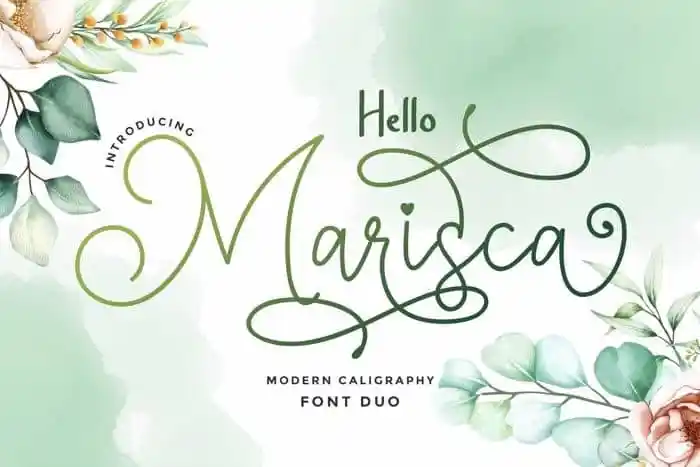
Hello Marisca Script Font – Fonte Grátis
Hello Marisca Script Font
Agora está disponível no mercado a “Hello Marisca Script Font”, uma elegante tipografia que pode ser interpretada de forma profissional. Este tipo de letra é perfeito para aqueles que desejam uma adicional de personalidade e sofisticação em seus projetos, permitindo uma mistura entre um script regular e várias alternativas de letras minúsculas para criar ligaturas únicas. A fonte foi criada e compartilhada pelo Designer Rantautype. Este tipo de letra moderna, feminina e atrativa está aqui para ajudá-lo a elevá-los a um novo patamar em seus trabalhos, sejam eles uma marca watermark na fotografia, um selo de assinatura ou até mesmo no logotipo. A “Hello Marisca” é perfeita para qualquer aplicação design, desde cartões de visitas e capas de álbuns, às citações e a criação de logos. O designer Deliyana está aqui para ajudá-lo a fazer deste projeto algo realmente especial. Com o “Hello Marisca Script Font”, você pode personalizar suas criações em uma variedade incrível de maneiras, garantindo que seu trabalho seja único e memorável.